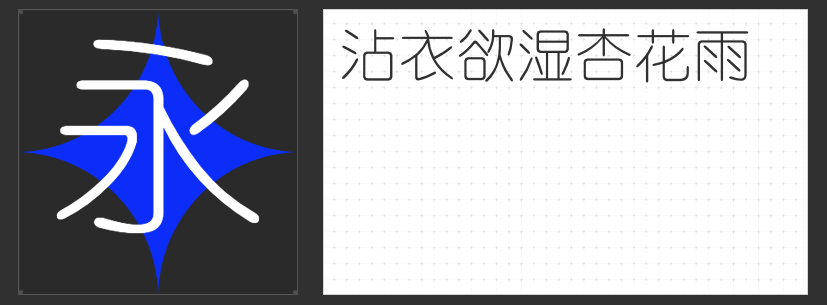
四款电商设计“点睛之字”:从视觉引力到品牌记忆的字体美学
在电商设计的视觉战场中,字体不仅是信息载体,更是品牌调性的无声代言人。一款适配的字体能在0.3秒内传递产品质感,在方寸间构建情感共鸣。本文精选四款风格迥异却皆具商业价值的字体,从屏显适配到节奏把控,为电商设计师提供多元化的美学解决方案。
一、励字志向黑简 大粗
这款融合圆体与黑体基因的字体,通过外圆角设计打破传统黑体的机械感,在保持字面充实、结构稳定的同时,为屏显场景注入呼吸感。其笔画粗细经光学补偿优化,确保在不同分辨率下仍能呈现均匀灰度,特别适合作为主标题字体,在促销海报、商品详情页头部等核心区域构建视觉焦点。圆角处理弱化了商业气息的锐利感,更易拉近与年轻消费群体的心理距离。
二、字恋狂漫野 鸣风
以直线为主体的手写风格字体,通过布白空间的精妙控制实现“乱中有序”的视觉韵律。笔画去钩设计与断点处理赋予字体呼吸感,大小错落的字型排列则模拟了真实书写时的自然节奏。这款字体适合用于文创产品、手作工艺等品类的详情页,其不完美中的精致感能有效传递“匠心”理念,在同类竞品中形成差异化记忆点。
三、励字综艺简繁
粗壮笔划与方正结构的组合,使这款字体在远距离仍能保持高识别度,其圆润拐角处理则避免了生硬感,在保持专业性的同时增添亲和力。在直播带货、闪购活动等需要快速传递信息的场景中,这款字体能通过强烈的视觉冲击力锁定用户注意力,特别适合作为价格标签、倒计时模块等关键元素的载体。
四、励字细圆简繁
清瘦纤细的笔划与正方形字面构成独特的几何美感,无衬线设计确保了小字号下的可读性。这款字体在高端美妆、3C数码等品类的详情页中表现尤为出色,其克制的设计语言能精准传递“精致”“科技”等品牌关键词,与极简主义视觉风格形成完美呼应。
这四款字体分别代表了力量感、温度感、专业感与精致感四大设计维度,设计师可根据产品特性与营销目标进行组合运用。在电商视觉同质化日益严重的今天,字体的选择已成为突破信息噪音、构建品牌认知的关键武器。